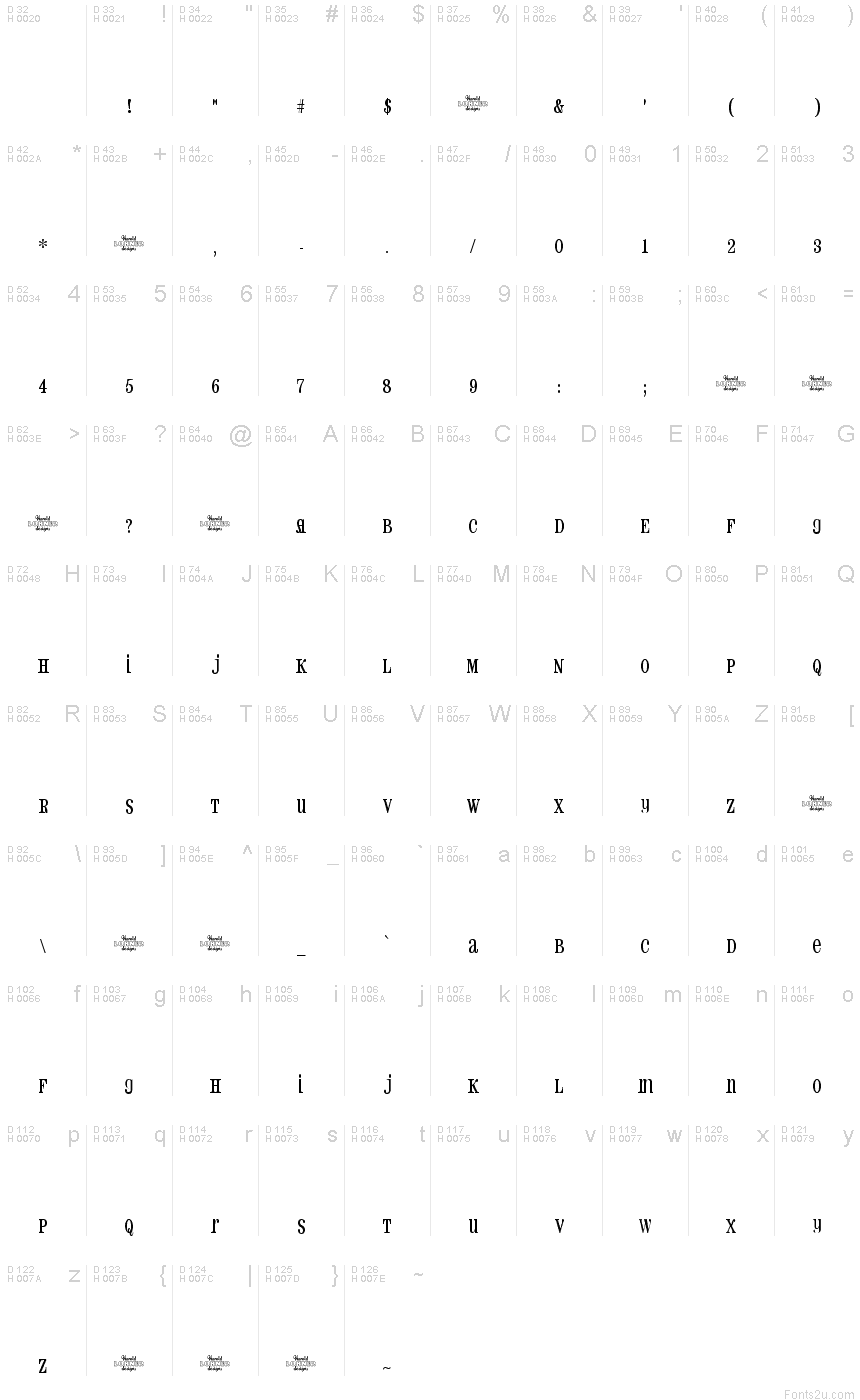
Pharmacy autorstwa Harolda Lohnera to darmowy szeryfowy krój pisma w stylu vintage, inspirowany dawnymi szyldami aptecznymi – ma w sobie ten specyficzny klimat starych witryn sklepowych, malowanego szkła i osiedlowych markiz. Litery łączą wyprostowaną, klasyczną konstrukcję z kilkoma teatralnymi akcentami, szczególnie w postaci wydłużonej ogonkowej „a” oraz wyrazistych, nieco formalnych szeryfów, które nadają alfabetowi aptecznego sznytu.
Krój świetnie pasuje do identyfikacji wizualnej barberów, sklepów z alkoholami, etykiet kawy czy zabytkowych witryn. Sprawdza się również na plakatach, przy rozpoczynaniu rozdziałów i w krótkich nagłówkach, gdzie ten charakter ręcznie malowanego szyldu może w pełni wybrzmieć. Jako darmowy font, Pharmacy najlepiej sprawdza się w nazwach, tytułach i monogramach, ponieważ jego dawny urok najszybciej udziela się w krótkich, wyeksponowanych tekstach.